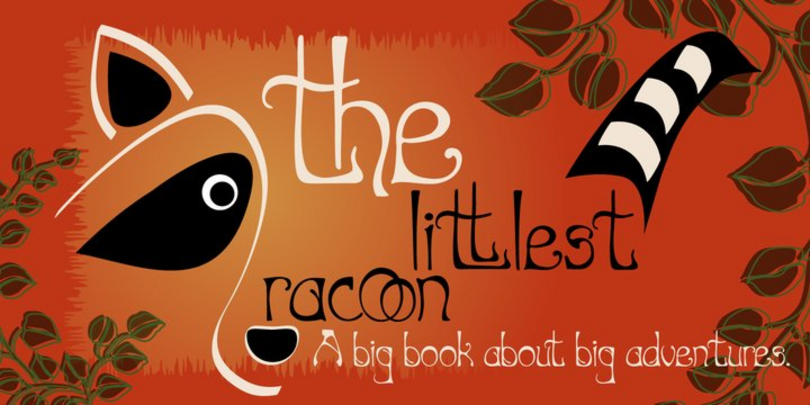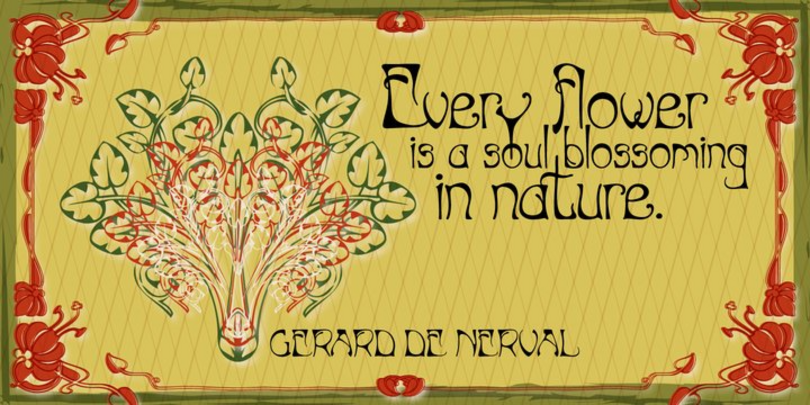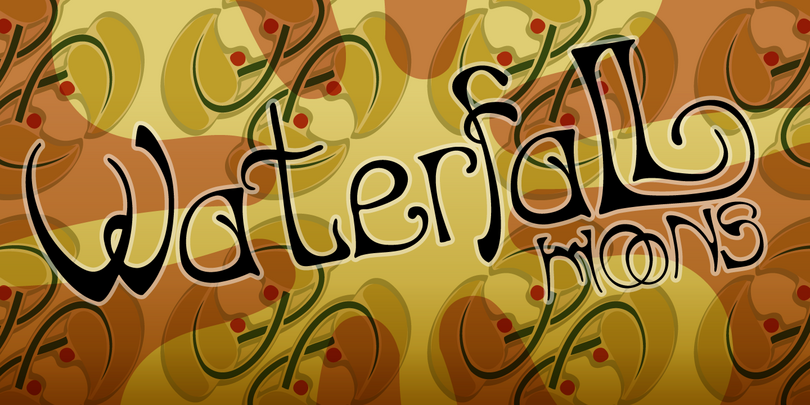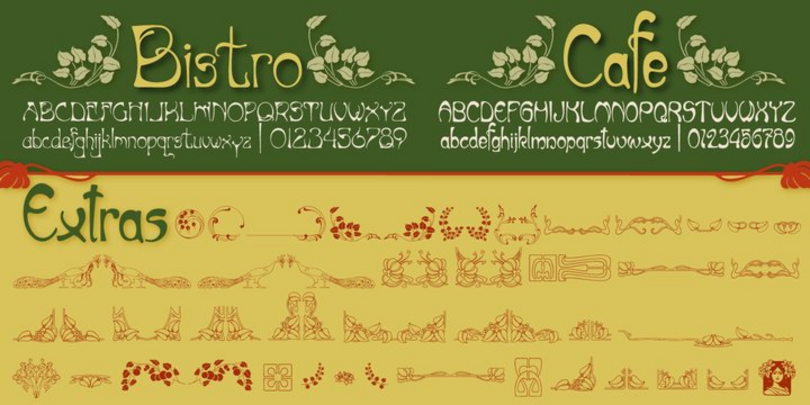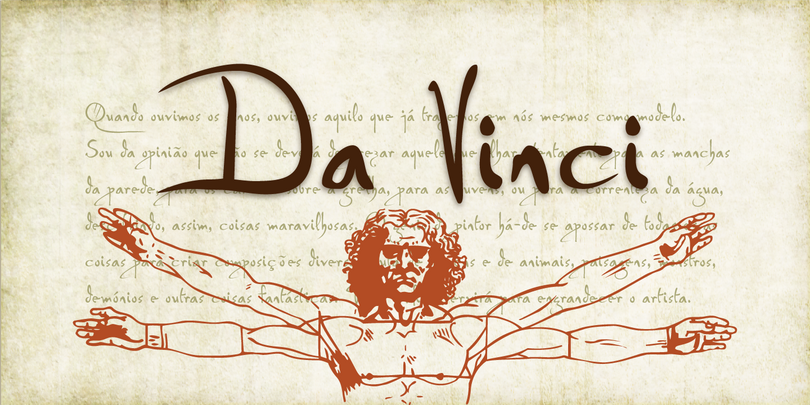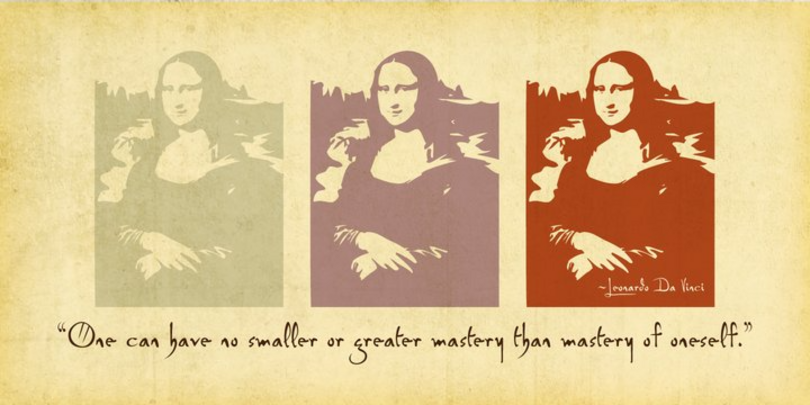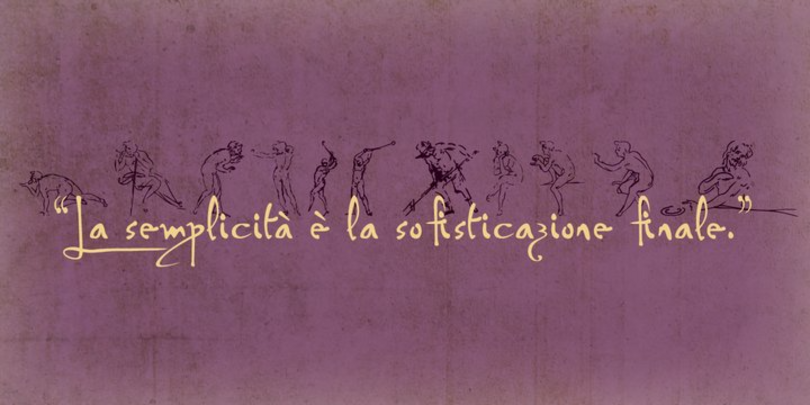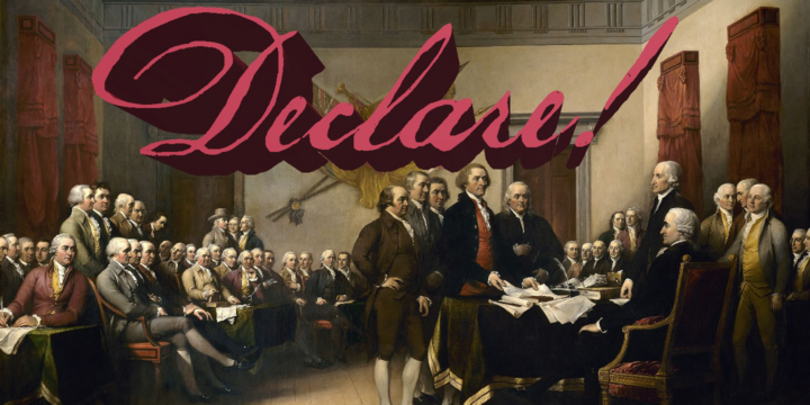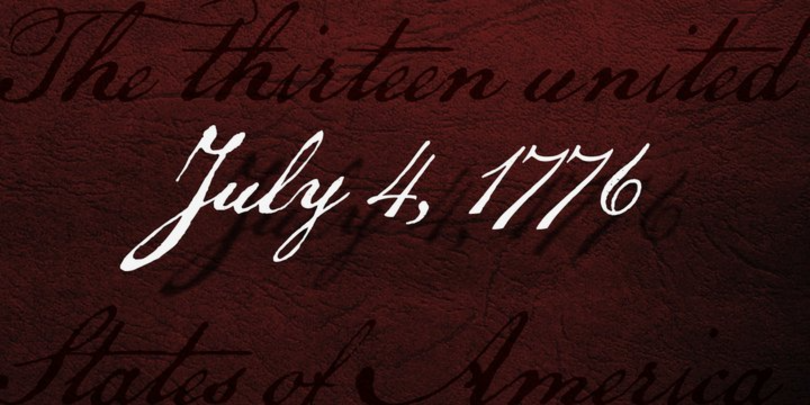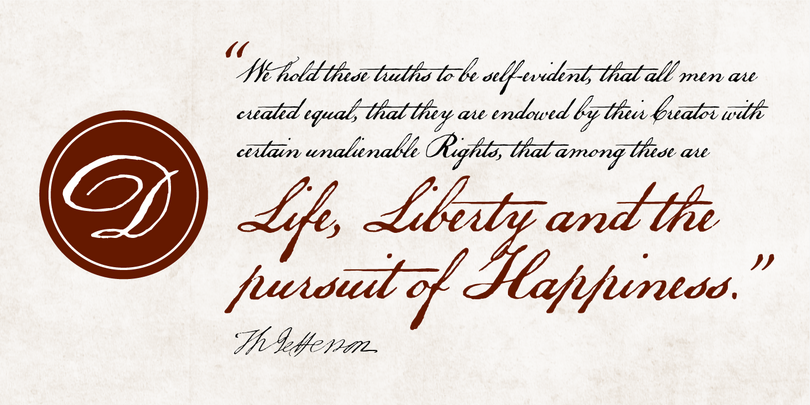
P22 Type Foundry.
P22 Type Foundry est une fonderie de caractères numériques et un atelier d'impression typographique basé à Rochester (New York) créé en 1994 par deux cofondateurs : Richard Kegler et Carima El-Behairy. Cette fonderie se spécialise dans la création de polices de caractères informatiques inspirées de l'art, de l'histoire et des sciences qui, sans elle, n'existeraient pas au format numérique. P22 se distingue par son travail avec des musées et des fondations comme le Guggenheim, le Musée du Transport de Londres, le Philadelphia Art Museum of Art et la Fondation Frank Lloyd Wright pour faire revivre avec précision ces dessins de lettres historiques. P22 propose également des collections spéciales, reposant sur son style typographique unique, notamment International House of Fonts, Lanston Type Co. et Hamilton Wood Type Collection.
P22 Underground
En 1916, le calligraphe Edward Johnston fut chargé de créer une police de caractères pour le métro londonien. Il proposa une police sans serif avec des proportions classiques. Ce concept unique pour l’époque devint une véritable icône du design graphique britannique. Après avoir obtenu une licence exclusive auprès du Musée du Transport de Londres en 1997, P22 a remis cette police au goût du jour, en gardant l’esprit du design d’origine et en conservant son système de proportions. En 2007, P22 a revu et étendu la collection en un vaste ensemble de caractères avec diverses hauteurs supplémentaires, une compatibilité linguistique étendue et quelques changements stylistiques. P22 a également ajouté une version Pro qui offre des alternatives de la police de caractères en italique ou en majuscules alternées, ainsi que des variantes « humaniste » et « géométrique ».
P22 Da Vinci
Léonard de Vinci, grand maître, inventeur et visionnaire italien a créé une variété extraordinaire d’œuvres qui continuent à susciter l’émerveillement de ceux qui les étudient. Cette famille de polices s’inspire de l’imagination remarquable de Léonard de Vinci et comprend une police exclusive Da Vinci Backwards (imitant le style d’écriture propre à l’artiste). Les 72 suppléments inclus sont tirés des carnets de croquis et des journaux de Léonard de Vinci.
P22 Posada
Le graveur mexicain Jose Guadalupe Posada (1851-1913) a créé une grande variété d’œuvres comme des journaux grand format, des cartes, des publicités et des affiches qui défendaient l’homme ordinaire et évoquaient les événements horribles et macabres de cette époque. L’artiste découpait souvent son propre lettrage pour qu’il ressemble à des versions plus décoratives des caractères gothiques en bois. La police de caractères P22 Posada a été conçue pour reproduire son visuel le plus remarquable : des « calaveras » (crânes) en célébration du Jour des morts. Les calaveras sont des effigies de personnes vivantes représentées comme des squelettes, qui accomplissent leurs activités quotidiennes avec humour et espièglerie, aidant à faire le lien entre ce monde et l’au-delà. P22 Posada offre deux polices de petites capitales et un style Extras contenant 60 images ludiques et effrayantes.
P22 Declaration
Le 4 juillet 1776, la Déclaration d’indépendance des États-Unis d’Amérique a été adoptée par le Congrès, et sa version préliminaire manuscrite a été envoyée à un imprimeur qui en a fait entre 150 à 200 copies. Quelques semaines plus tard, une copie conforme a été calligraphiée sur parchemin pour que les délégués la signent. La police P22 Declaration s’inspire de cet exemplaire calligraphié. La famille est composée de six styles dont une police ayant l’aspect de la calligraphie du XVIIIe siècle, avec un bord légèrement irrégulier, comme on en trouve sur les documents rédigés avec des plumes d’oie et de l’encre sur du vélin ou du parchemin, et une police d’accompagnement Blackletter qui était utilisée afin de mieux faire ressortir certains éléments du document original et pour le titre. Une troisième police reproduisant les signatures des parties au document est également incluse.
P22 GD&T Geometric Dimensioning and Tolerancing
Le Tolérancement Géométrique et Dimensionnel (GD&T) est un système permettant de définir et de communiquer des tolérances techniques. Elle utilise un langage symbolique sur les dessins d’ingénierie et les modèles solides tridimensionnels générés par ordinateur qui décrivent explicitement la géométrie nominale et ses variations autorisées. La police de symboles de P22 est conçue spécifiquement pour que les ingénieurs l’utilisent afin de décrire la conception assistée par ordinateur (CAO) produite en dehors de l’environnement CAO. La police de caractères comprend un tableau présentant les noms des caractères et leur emplacement sur le clavier, elle inclut le symbole « unilatéral » ajouté au système en 2009 et respecte la norme ASME Y14.5M-1994.
P22 Art Nouveau
Le courant art nouveau de la fin du XIXe siècle proposait une approche audacieuse des lignes organiques et une décoration somptueuse. Ce nouveau style s’est répandu à travers le monde, marquant l’entrée dans une nouvelle période qui a conduit à l’art moderne et au design. La famille de polices P22 Art Nouveau inclut trois styles différents : Bistro, Cafe et le style Extras qui contient 97 caractères fleuris.
P22 Kells
Le Livre de Kells est un gospel du IXe siècle créé dans les îles britanniques et considéré comme le plus bel exemple d’art celtique. Le livre en lui-même est désormais exposé dans la bibliothèque du Trinity College à Dublin, en Irlande. P22 Kells est un jeu de polices informatiques qui allie précision historique et lisibilité fonctionnelle dans deux styles différents (rond et carré) et comporte 72 éléments et bordures de liaison.
P22 FLW Midway
Cette police s’inspire de l’écriture du célèbre architecte Frank Lloyd Wright, retrouvée sur les dessins d’exécution des Jardins Midway de Chicago en 1913. Ce type de lettrage architectural est un peu plus décontracté que celui qui apparaît sur la plupart des plans. Il évoque la personnalité de Frank Lloyd Wright et vient compléter les autres polices de la série P22 FLW Midway. Midway One et Midway Two, qui ont toutes deux été repensées et contiennent plus de 400 caractères, peuvent être utilisées de manière interchangeable pour offrir un aspect d’écriture manuscrite plus naturel. Midway Ornaments comporte quant à elle plus de 100 éléments de bordure décoratifs combinables de nombreuses façons pour obtenir des motifs décoratifs surprenants et efficaces.
P22 Victorian Gothic
P22 Victorian Gothic est une famille de polices créée en partenariat avec l’exposition de la Galerie d’Art Albright-Knox consacrée à l’artiste français de l’ère victorienne James Tissot. Les polices issues de ce jeu s’inspirent de polices de caractères historiques datant de la fin du XIXe siècle. Victorian Gothic est basée sur un style de caractères appelé « Atlanta » : une police simple, de largeur étendue, originale, mais élégante, semblable à « Copperplate ». Victorian Swash reprend les caractéristiques de « Columbian », une police mince et délicate, également connue ces dernières années sous le nom de « Glorietta », mais y intègre des ornements « ajoutables » basés sur les motifs originaux de Columbian. Victorian Ornaments comprend plus de 150 ornements décoratifs.
P22 Marcel
Cette police est nommée en hommage à Marcel Heuzé, un Français réquisitionné pour travailler en Allemagne pendant la Seconde Guerre mondiale. À cette période, il écrivit des lettres à sa femme et à ses filles qui contenaient de rares témoignages rédigés à la première personne racontant le quotidien de la survie dans des camps de travail. Il y exprimait aussi les plus belles déclarations d’amour imaginables. Ces documents originaux ont servi de source pour créer une police cursive qui reproduit les caractéristiques expressives de sa propre écriture. Offrant une très bonne lisibilité, cette police reprend des détails de texture qui imitent l’aspect de l’encre sur le papier. Marcel Caps est une police manuscrite conçue pour le titrage en association avec Script, tandis que Marcel EuroPost One et Two présentent chacune plus de 200 cachets, oblitérations et marques de censure historiques.